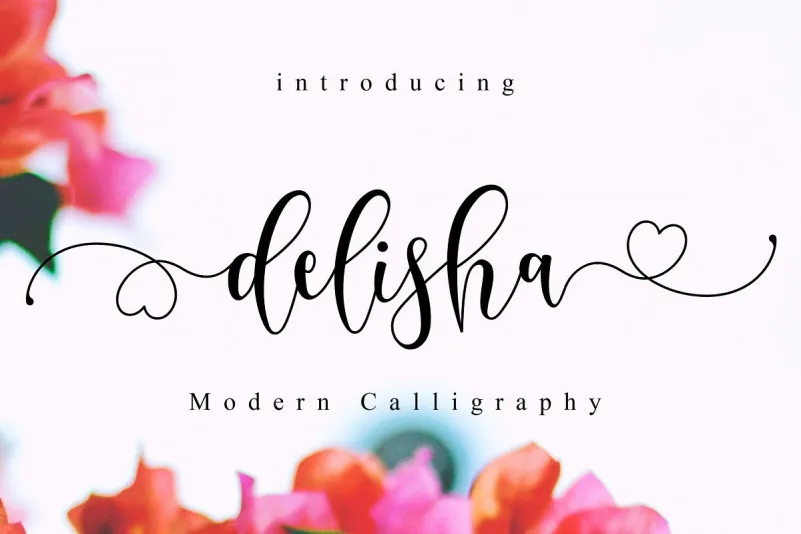
Delisha – Lovely Script Font – Download Grátis
Aqui está uma descrição em português para a página de download da font ‘Delisha – Lovel Script Font’: Introduzimos Delisha, uma nova fonte de script que se apresenta como um belo complemento para seu trabalho criativo. Esta fonte, ideal para cartões, impressões, convites e ilustrações decorativas, é perfeita para aqueles momentos especiais do ano em que você quer transmitir a essência de uma escrita manuscrita. Delisha traz um conjunto único e encantador de caracteres, complementado por ligaturas estilizadas. Esta fonte natalina não apenas adicionará um toque elegante aos seus projetos digitais ou impressos, mas também oferece um aspecto moderno que pode ser usado em várias aplicações gráficas, incluindo logotipos, marcações, convites e estaçãoários. Delisha é uma fonte de script perfeita para aqueles momentos especiais onde uma escrita manuscrita faz a diferença. Suas linhas elegantes e modernas podem ser usadas em qualquer projeto que exija um toque autêntico da mão. Não deixe esta bela fonte passar por você, ela será uma adição inegável à sua coleção de ferramentas gráficas. Delisha é uma escolha ideal para aqueles que desejam dar um toque único e especial a suas publicações nas redes sociais ou em qualquer outro projeto. A sua harmonia com fontes serifadas também faz dela uma opção versátil. Não hesite em adquirir Delisha e experimentar como ela pode revolucionar seus projetos de design.